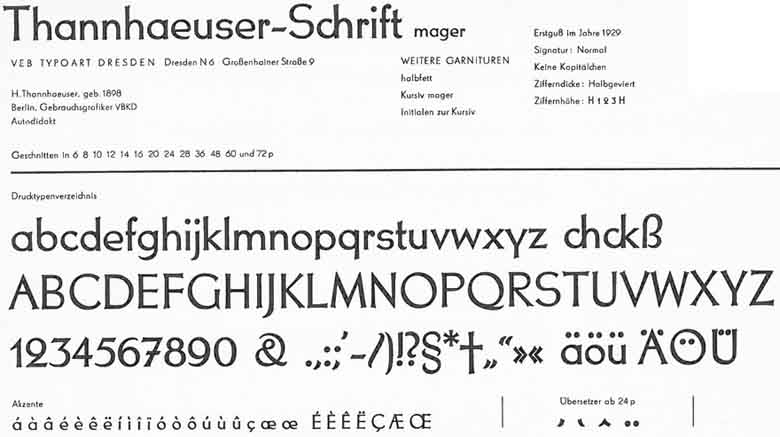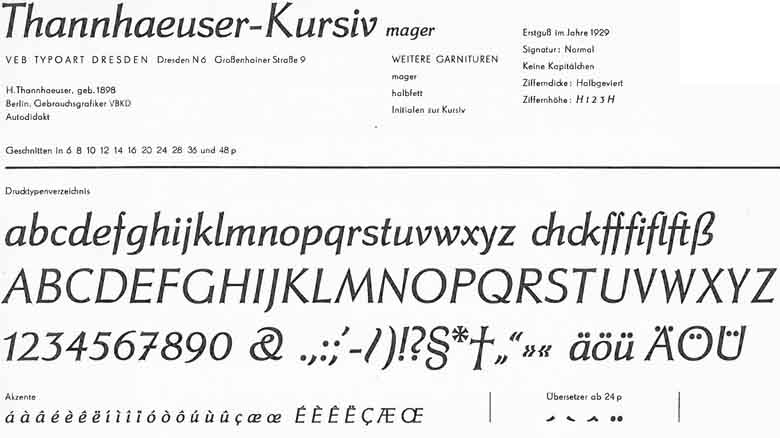
Versalien gemischt mit Minuskeln
gibt es eine Schrift, deren Versalien eine Mischung aus echten Versalien und Minuskeln ist, die dieselbe Versalhöhe haben?
ich möchte diesen alten Beitrag mal ausgraben, weil ich die gleiche Frage habe, wie oben schon Nanadia:
„Gibt es eigentlich auch Unicase oder andere Fonts, bei denen die Umlaute in Versalien die gleiche Versalhöhe haben wie die anderen Zeichen?“
Die tolle Lausebengel hat sowas! :hammer: Wobei das mit Versalien und Unicase-Schriften zwei ganz unterschiedliche Fragen sind bzw. sein können. Um welche geht es dir speziell? Beides trifft auf diese zu: http://myfonts.us/td-OuzIcC Versalschriften, die als Title-Case-Version oder Stylistic Alternate die Umlaute runterziehen gibt es ja ein paar.
Bei Bleisatzschriften war es durchaus üblich, daß die Umlautpunkte so in die Großbuchstaben eingebaut waren, daß diese dadurch nicht höher wurden. Leider sind bei den digitalisierten Schriften oft einfach die Umlautpunkte übergesetzt. Ein Beispiel dafür ist die Futura. Während es in den meisten digitalen Futura-Fassungen nur die übergesetzten Punkte gibt, hat die 20th Century von der Lanston Type Company (ein Futura-Klon) die ursprünglichen Umlaute:
Die Thannhaeuser (Antiqua) in Blei hatte nach meiner Erinnerung auch soetwas: da waren die Punkte sehr lustig im Kreis vom Ö. In der digitalen Variante der "Neuen Thannhäuser" ist das aber leider nicht mehr so ...